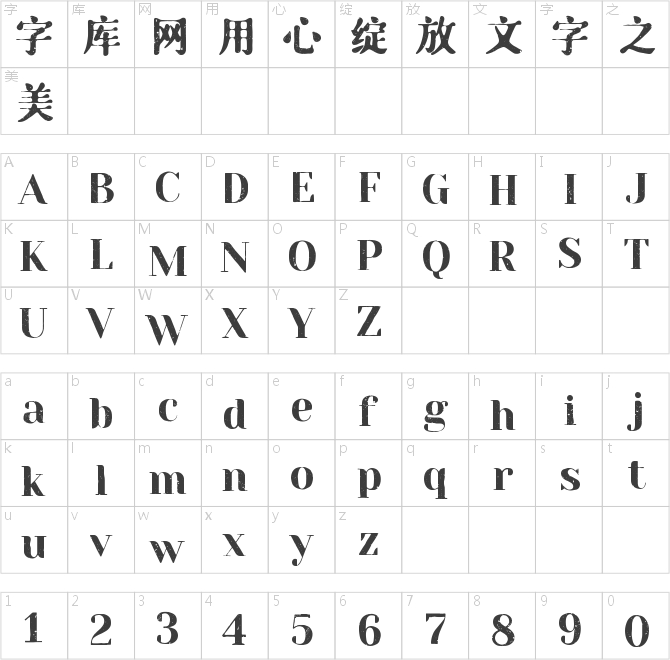
字魂213號-琉璃宋
字魂213號-琉璃宋是一款創意衍生字。字體筆畫進行了特效處理,增加了一絲復古風,字體筆觸舒展流暢,粗細均勻,轉折處婉轉有度,適用于報刊、書籍的各類標題字。
字魂213號-琉璃宋字體zihun213hao-liulisong字庫是一款讓人賞心悅目、百看不厭的中文字體,適合各類廣告和產品包裝設計應用,字體大小32.78MB,格式為ttf字體,上傳用戶是黃肖,作者/版權方為字魂